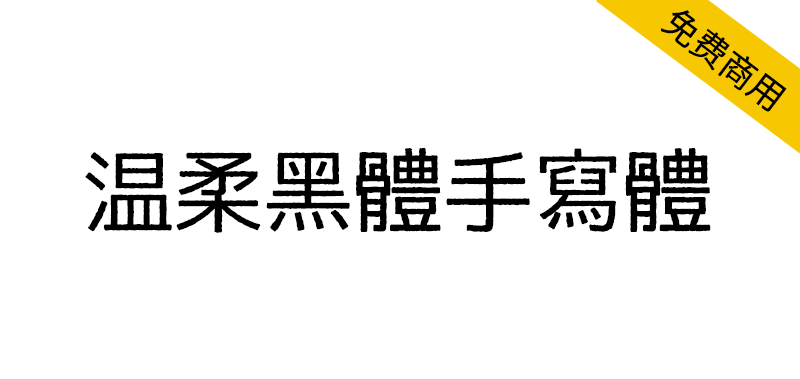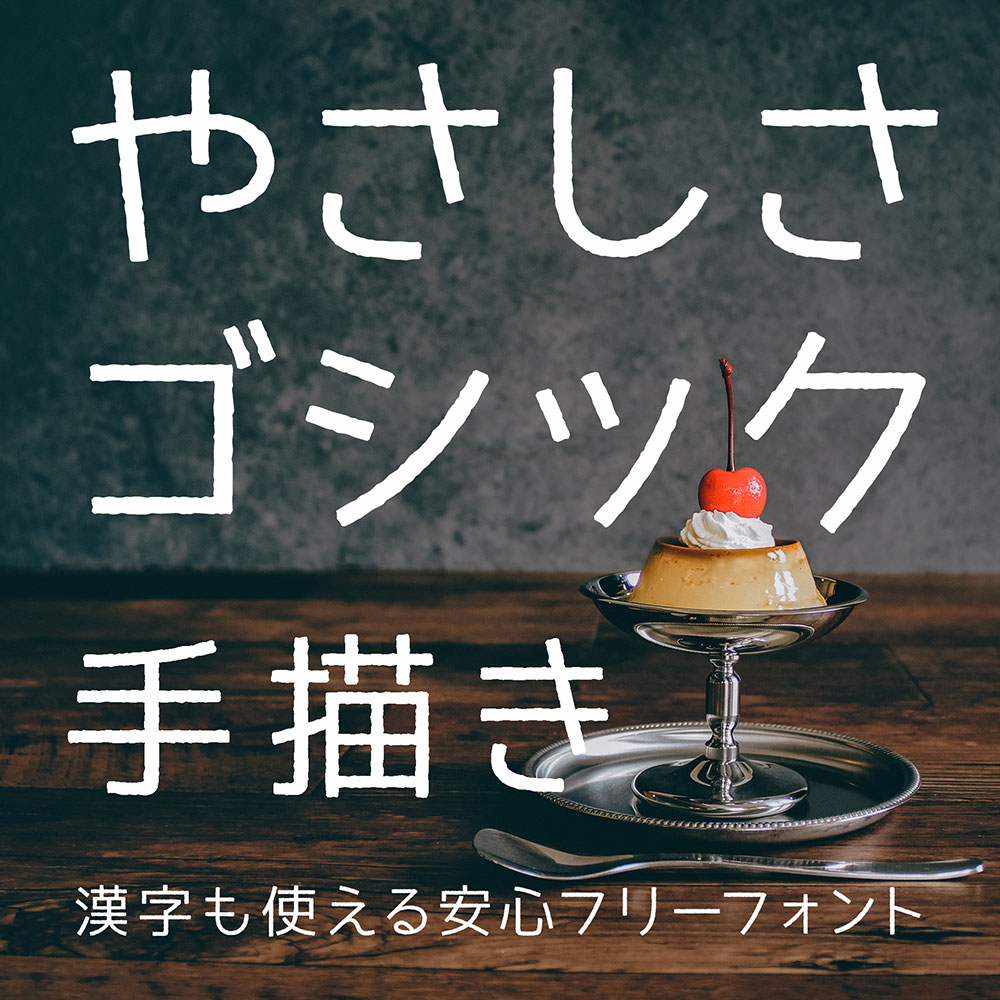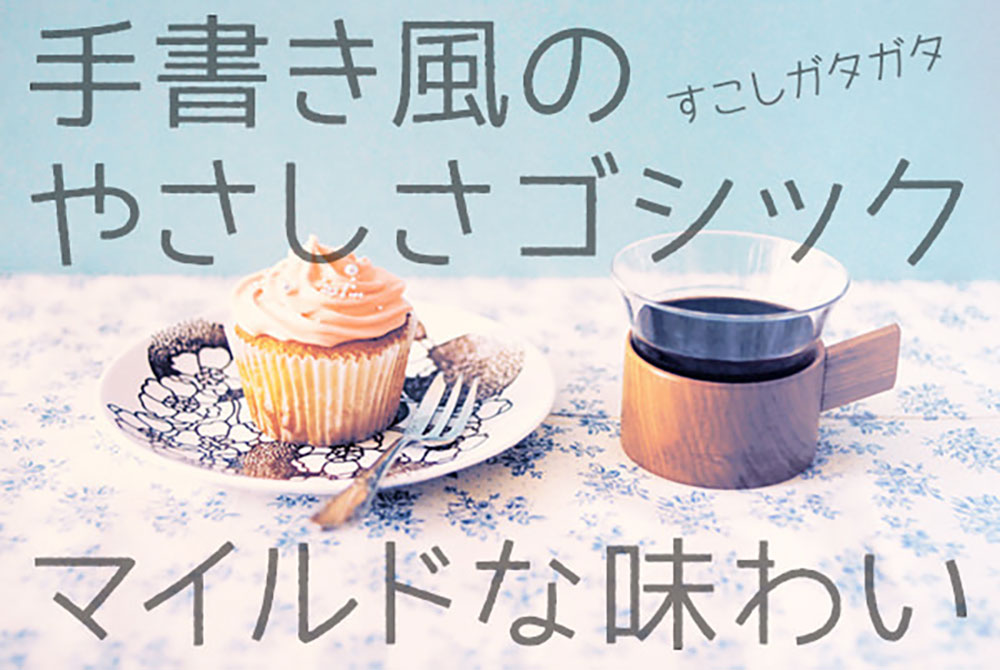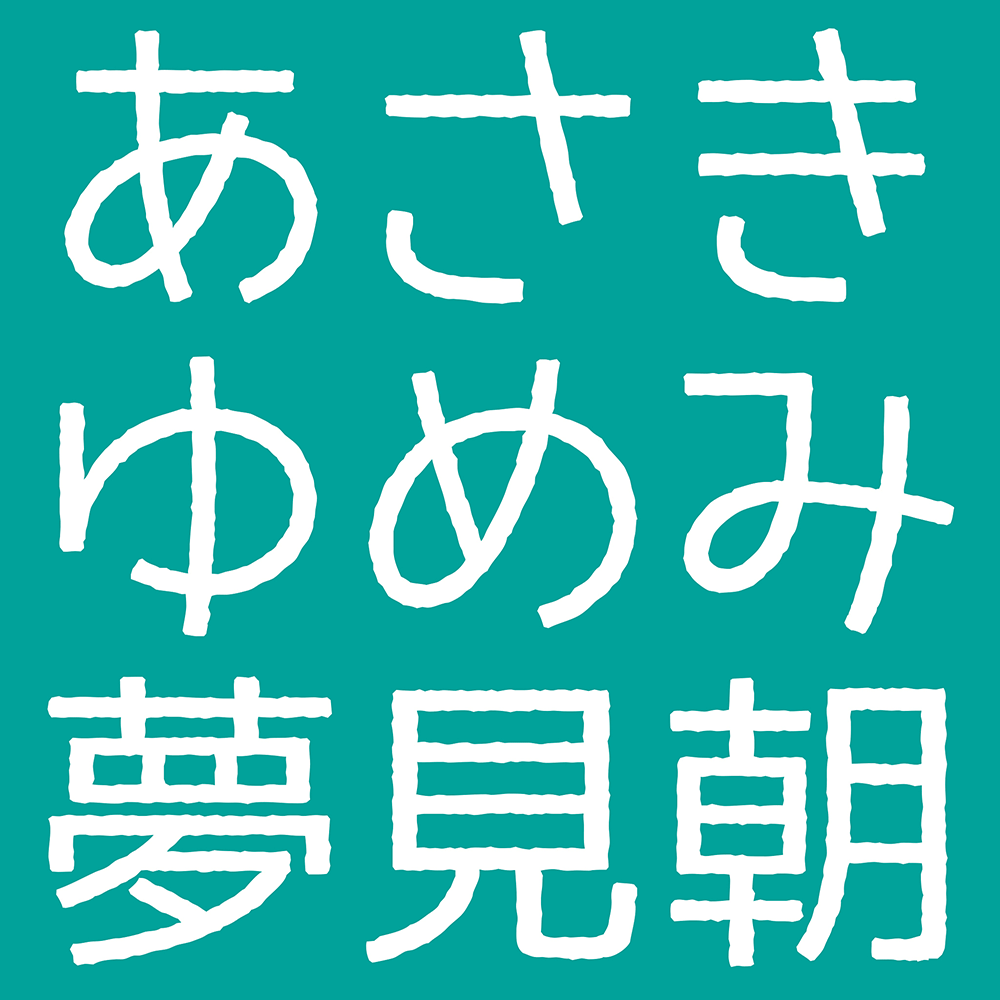
温柔黑体手写体(やさしさゴシック手書き)是一款在"温柔黑体"基础上加入手写风格、略带斑驳线条的字体。特别适合需要为标题或标语增添手工温暖感的场景,正文内容建议使用常规版温柔黑体更合适。
やさしさゴシックに手書きの風合いを加えた、少しガタガタした線のフォントです。見出しやタイトルに、ちょっと手作りの優しさを加えたいときなどに役に立ちます。本文には通常のやさしさゴシックの方が向いていると思います。このフリーフォントをご使用になるには、ダウンロードファイルに含まれる「M+FONT-TESTFLIGHT」「IPAフォントライセンス」の内容を読みください。